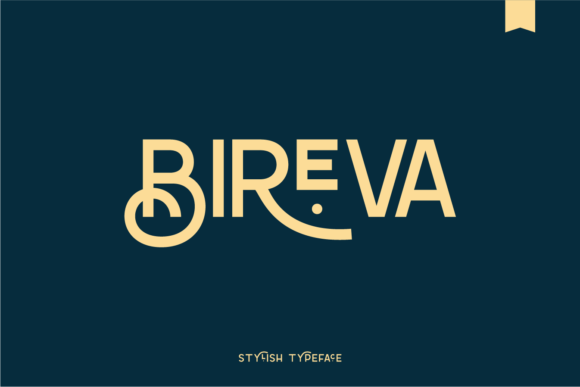
Creativefabrica Beriva Font
[Creativefabrica] Beriva Font
Beriva - это органический и уникальный шрифт без засечек.
Его легко подогнать под невероятно большой набор проектов, поэтому добавьте его к вашим творческим идеям и заметьте, как он выделяет их на фоне других!